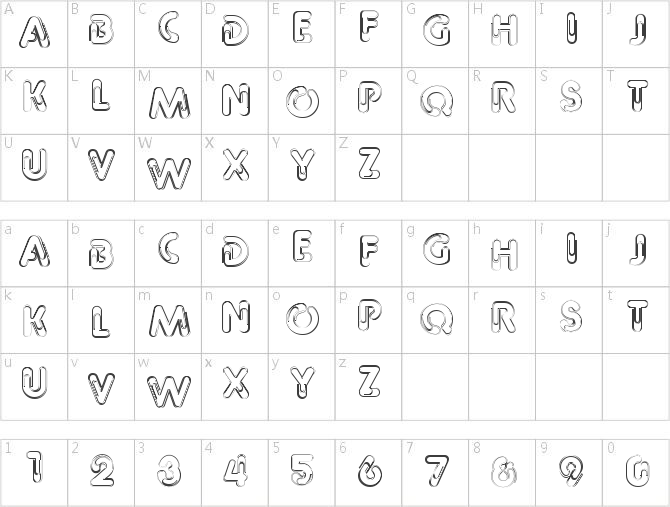
Paper Clip Outline 詳情頁
字體名稱: Paper C
Paper Clip Outline
Paper Clip Outline字體字庫是一款讓人賞心悅目、百看不厭的英文字體,適合各類廣告和產品包裝設計應用,字體大小0.09MB,格式為ttf字體,上傳用戶是gagilang,作者/版權方為未知